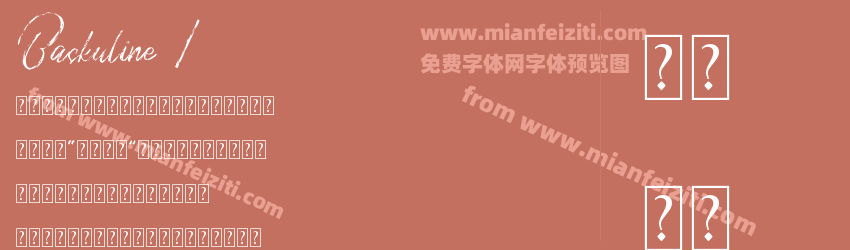
Baskuline 1
字体名称: Baskuline 1
Postscript名称: Baskuline1
Baskuline 1预览图1
Baskuline 1预览图2
Baskuline 1字体映射图
本款“Baskuline 1”是一款书写很新颖的字体,字体大方,适合各种设计作品使用!欢迎下载!